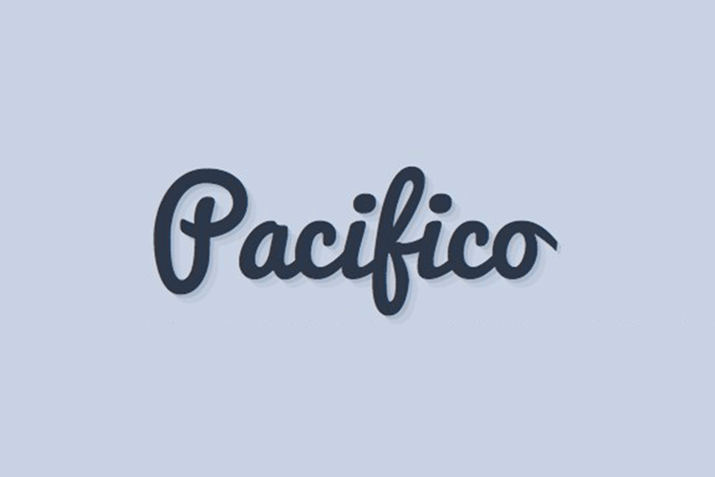
The 10 Best Script and Handwritten Google Fonts
10 script und hangeschriebene Fonts auf Google Fonts
Alle Schriften werden mit einer einzigartigen CSS-Behandlung angezeigt (und mit dem Code geliefert, den Sie für eine schnelle Implementierung benötigen!). Sie werden auch alle mit Google Fonts serviert, sodass Sie mit einem schnellen Kopieren und Einfügen sofort einsatzbereit sind, ohne dass Downloads erforderlich sind!
Eine schön dicke Schrift mit guter Lesbarkeit und interessanten Buchstabenformen. Perfekt für Überschriften.
Lobster braucht keine Einleitung, es ist in den letzten Jahren zu einem der allgegenwärtigsten Skripte auf dem Planeten geworden. Version zwei bietet Ihnen die Wahl zwischen fett und dünn.
Ich liebe wirklich die ornamentale Natur dieser Schriftart, die Buchstaben sind groß, fett und wunderschön geschwungen. Verwenden Sie dies, wenn Sie ein altes Weltgefühl vermitteln möchten.
Merienda ist nicht mein Favorit, aber es hat sicher seine Verwendungsmöglichkeiten. Die Buchstaben haben ein gebürstetes Gefühl mit scharfer Richtung, das Bewegung gut vermittelt.
Pacifico ist einfach eine großartige, runde und geschwungene Schrift, die wirklich ein einzigartiges Gefühl vermittelt. Es ist schwer, eine dicke Schrift mit so schönen Kurven und so viel Charakter zu finden, also vergewissern Sie sich, dass Sie diese bookmarken.
Wenn Sie nach etwas suchen, das wirklich handgeschrieben aussieht, ist Just Another Hand eine gute Wahl. Um einen visuellen Effekt zu erzielen, habe ich Schatten verwendet, um ihm einen 3D-Effekt zu verleihen, aber es sieht großartig aus (oder sogar besser), auch ohne sie.
Arizonia hat ein fantastisches fließendes Gefühl mit breiten Bögen und sanften Strichen. Es ist eine großartige Logo-Schriftart und fühlt sich wirklich nicht wie etwas an, das man als live Webfont erwarten würde.
Cookie hat eine Art femininen Märchencharme, der es zu einer großartigen Schrift für Story-Überschriften und Ähnliches macht. Das nächste Mal, wenn Sie eine verspielte Note benötigen, sollten Sie es ausprobieren.
Great Vibes ist eine sehr kunstvolle Schrift wie Arizonia, aber etwas dünner und raffinierter. Die Buchstabenformen sind wirklich schön und ziehen sicherlich Aufmerksamkeit auf sich.
Leckerli One ist fett und zweckmäßig. Es ist ziemlich maskulin, soweit Schriften gehen, und perfekt für große, kühne Aussagen.
Da haben Sie es, zehn großartige Script- und handgeschriebene Schriftarten, servierfertig und bereit zur Implementierung. Die Google Font-Bibliothek hat weit über hundert davon, aber viele davon lohnen sich wirklich nicht, sie überhaupt zu verwenden. Hoffentlich hilft Ihnen dieser Artikel dabei, die Spreu vom Weizen zu trennen.